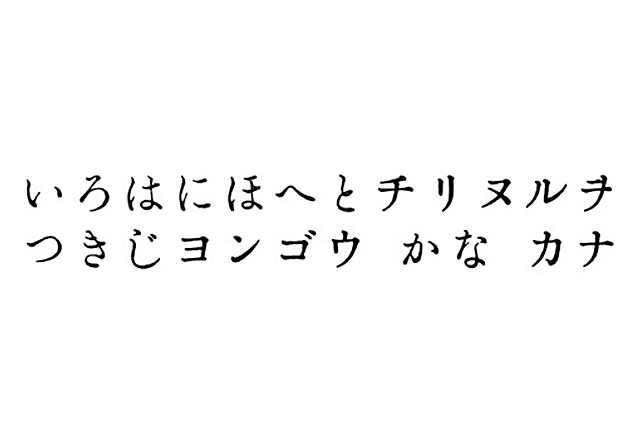
GL-築地四号 (築地体・四號片平假名)は、明治時代の東京築地活版製造所の書体を復元したフォントです。築地体、築地明朝体などと呼ばれています。GL-築地三号 (築地体・三號片平假名)よりもかっちりとした仕上がりです。ひらがな、カタカナ、記号が収録されています。
| 作者・シリーズ | Gutenberg Labo |